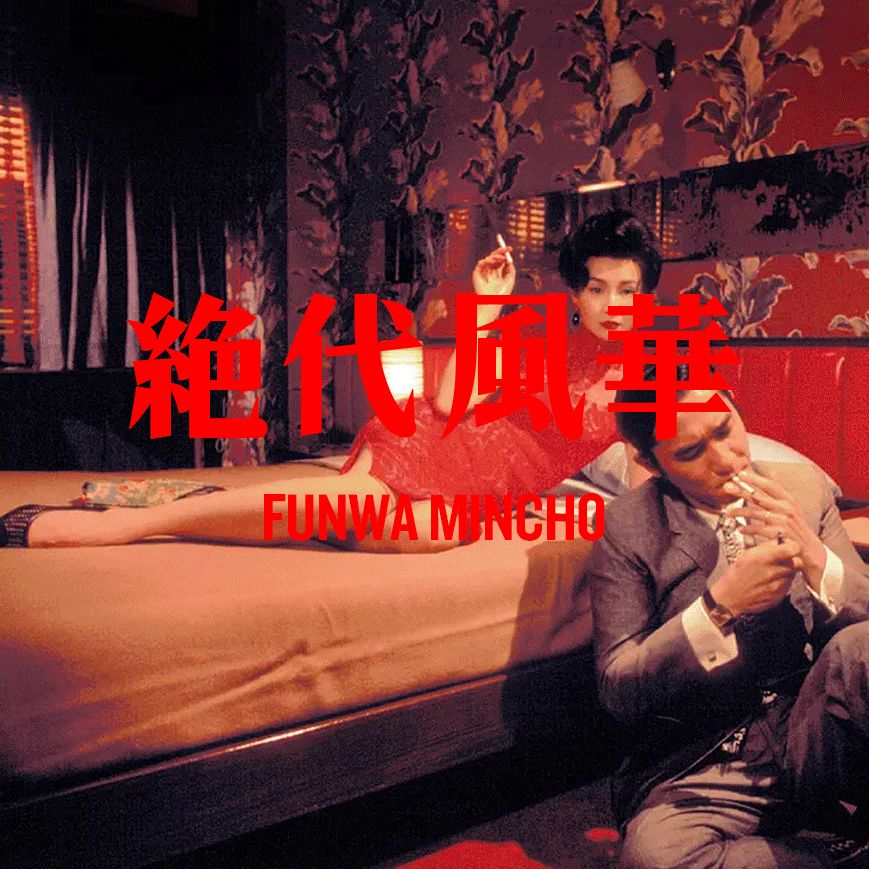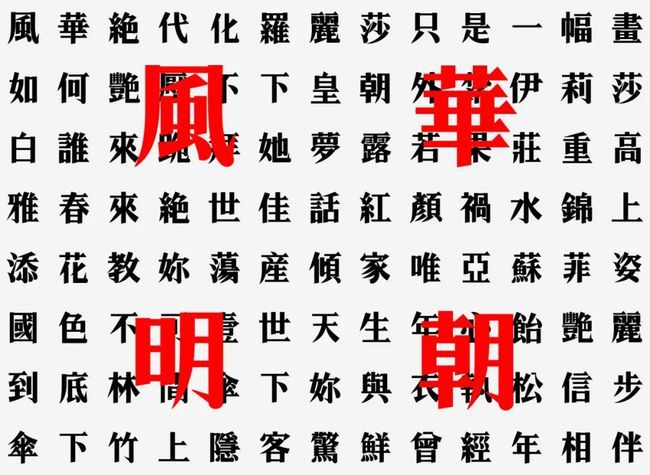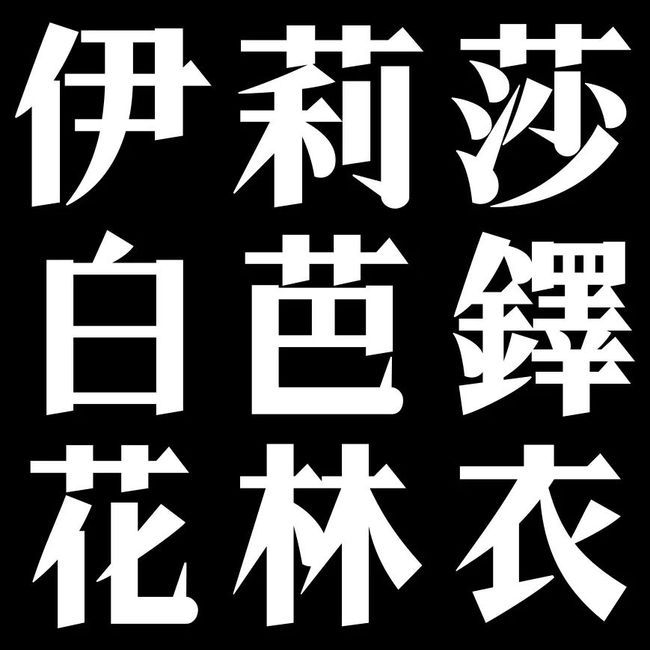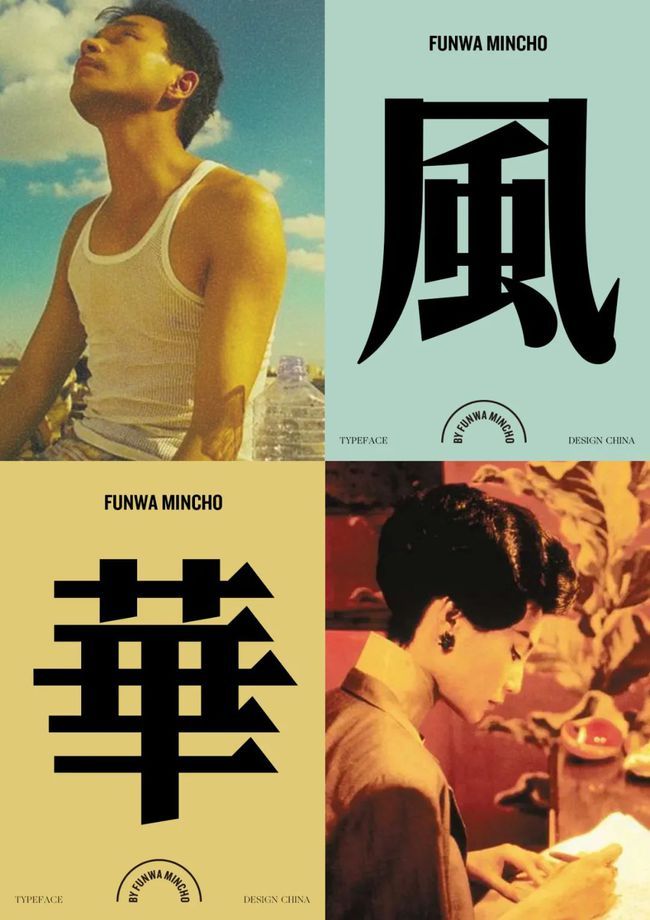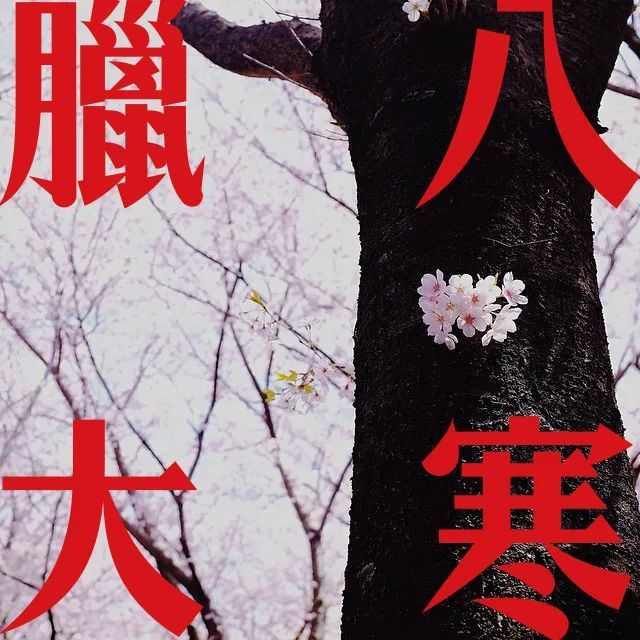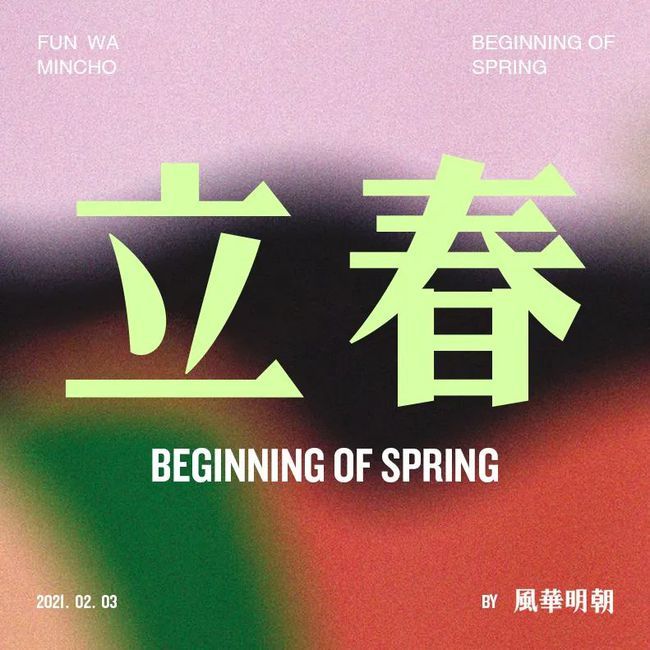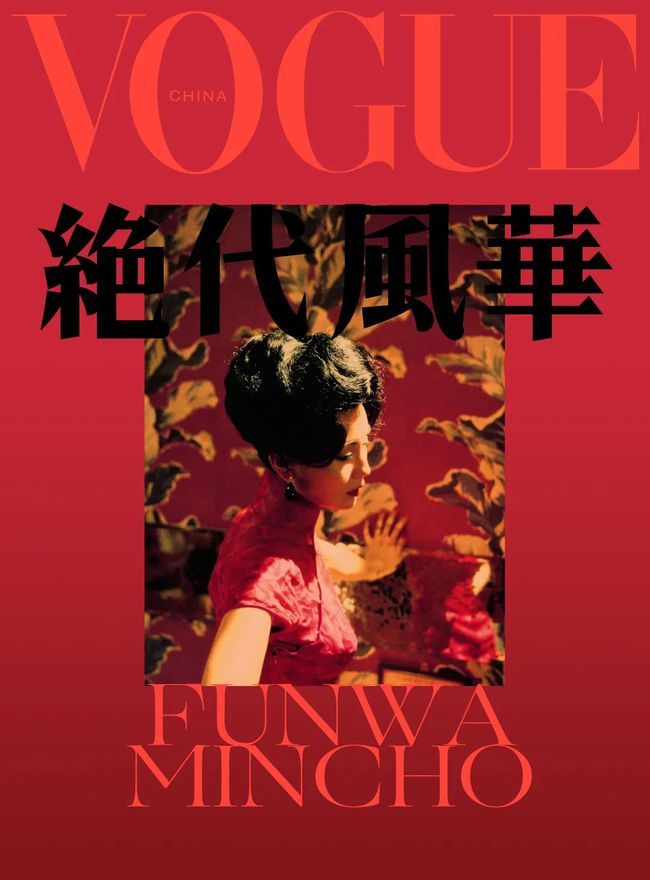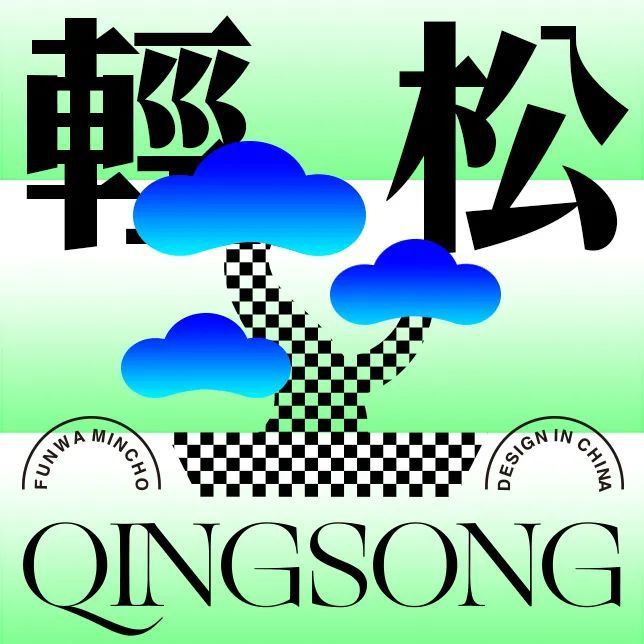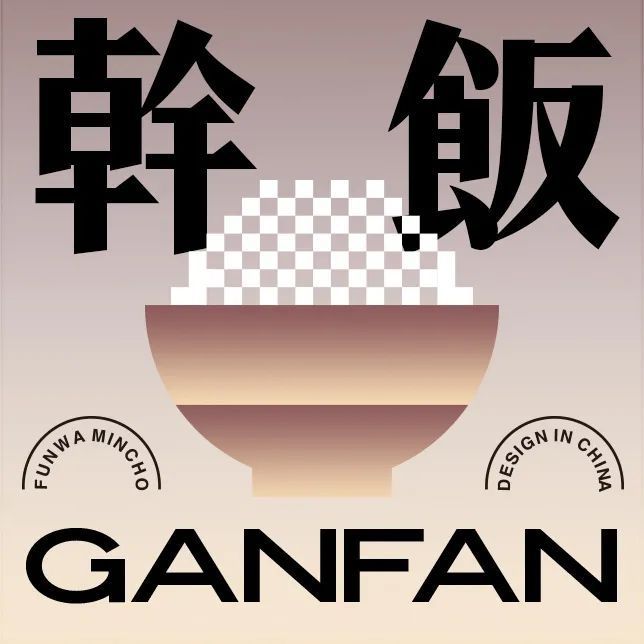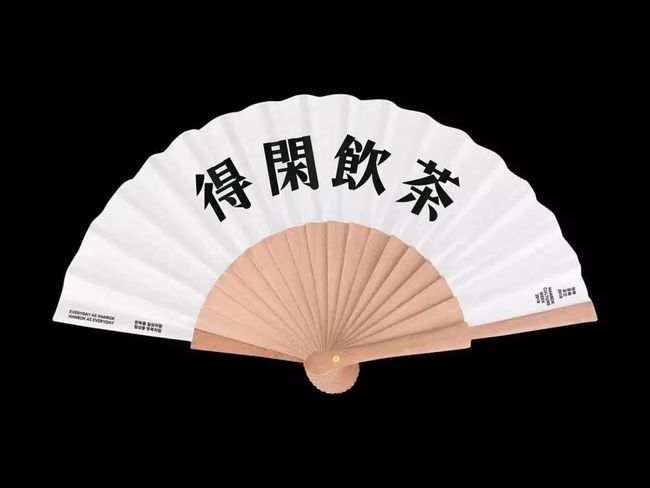
风华明朝(Funwa Mincho )由Typeschool和乐字制造共同开发,这是一款极具高雅时尚感的明体字型,旨在为时尚行业提供更优雅的标题用字,提升阅读的视觉体验。
风华:意指风采才华,雅丽、优美。语出南朝钟嵘《诗品》卷中:至如欢言酌春酒,日暮天无云,风华清靡,岂直为田家语耶!
风华明体字型上参考了香港电影《花样年华》海报字型,并以60年代初旧上海美术字型为蓝本进行创作。字体保留了明体的气韵、优雅,增添了一份时尚感。整体字形设计得略偏修长,让字型在视觉上更加高雅时尚,。
风华明体笔划挺拔有力,彰显文字的优雅,这正是字型的设计初衷。在物料及包装的应用上,我们都能感受到这种新字型所带来的美感。
笔画横细竖粗,身段高阔明朗,重心平稳,满足观众获取信息的流畅度。在保留明体风格的同时更显高雅端庄,经典而不失时尚感。
很多人觉得,外文杂志或西文字体的排版,无论是字与字的关系,还是整体呈献,都有恰到好处的组合,看上去有种难以言喻的时尚感。而汉字因为外形结构过于方正复杂,被许多人误认为很难排出高级感。
这主要是设计师缺乏对中文字结构的认识,忽略了汉字本有的韵律美,导致美感缺失。汉字是设计师日常排版中都会遇到问题,只有掌握了汉字的结构及韵律节奏,才能去更好的驾驭它。中文字体,也能具有高级感和时尚感!